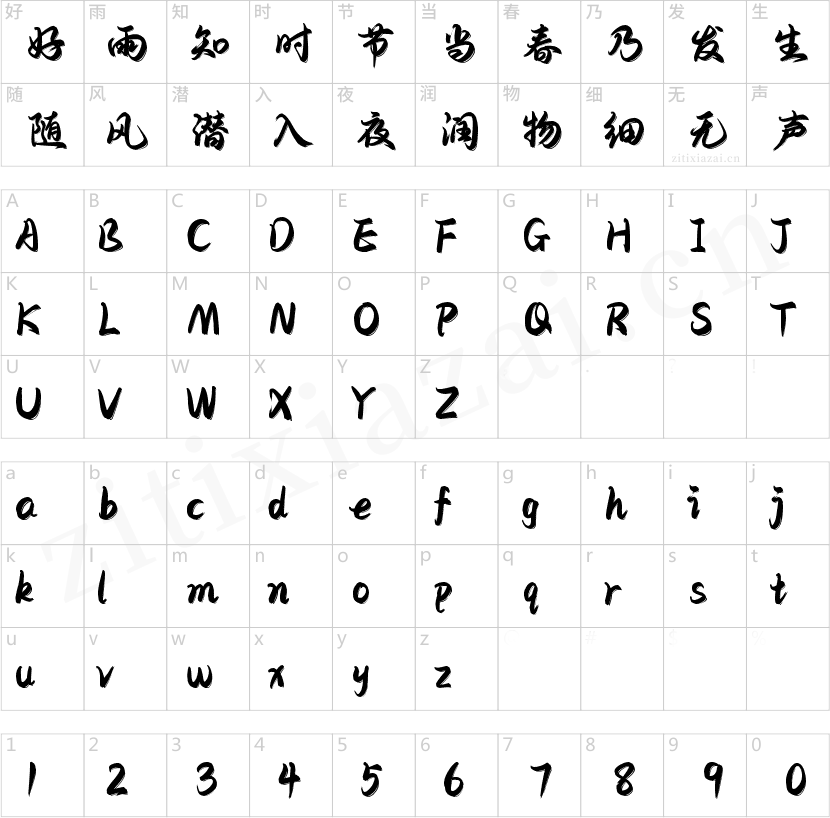
Aa后浪行楷
Aa后浪行楷,这款字体结构工整、笔画清晰,兼顾美观与易读性,适用于标题、正文、海报、包装、LOGO 等多种场景。字形优雅稳定,风格百搭耐看,适配日常排版与创意设计,让文字呈现更舒适、更具质感。Aa后浪行楷一笔一画,皆是细节,以均衡的比例、流畅的线条打造舒适视觉体验,字形端正大气,风格简约现代。无论是商业设计、品牌宣传还是日常排版,都能轻松驾驭,让文字更有格调与力量。Aa后浪行楷字体下载。
Aa后浪行楷字体
Aa后浪行楷是一款非常具有艺术性的字体,它的设计灵感来源于对古典艺术的研究,同时又融入了现代字体设计的元素。字形优美,笔画粗细变化自然,给人以大气、典雅的感觉。Aa后浪行楷是一款既传统又现代的字体,它的设计充满艺术感,美观大方,实用性也非常强。无论是对于设计师还是对于普通读者来说,都是一种非常不错的字体选择。Aa后浪行楷适合用于具有艺术感的场合,比如海报、宣传单张、书籍封面等。由于其字形流畅且具有动态感,也适合用于大量的文本排版,如报纸、杂志等。